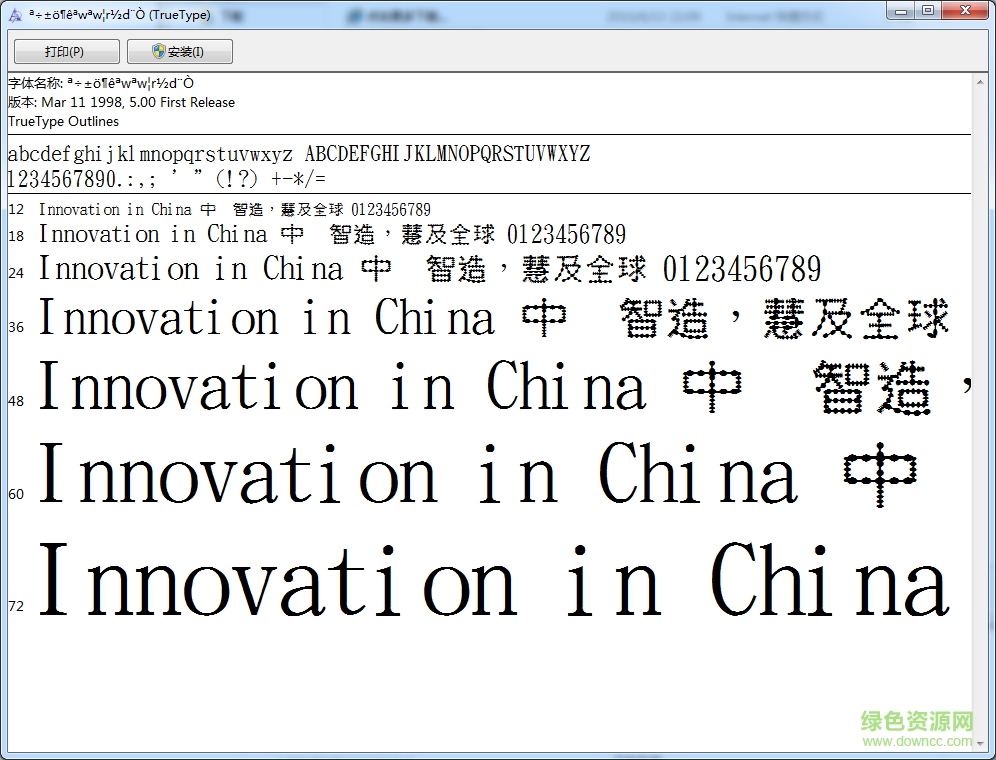
金梅圓泡泡字范例是一款非常有個(gè)性的金梅字體類型,以圓點(diǎn)鏈接的方式來展示字體,字體大方得體彰顯個(gè)性,非常實(shí)用便捷。快來綠色資源網(wǎng)下載體驗(yàn)吧!
金梅圓泡泡字范例是一款極具個(gè)性的中文藝術(shù)字體,該字體比較特別之處在于每個(gè)字都有許多泡泡的形狀組成,看起來非常的美觀大方,整體上結(jié)構(gòu)十分出眾,可以廣泛地應(yīng)用于廣告設(shè)計(jì)、影視制作以及海報(bào)設(shè)計(jì)等領(lǐng)域。